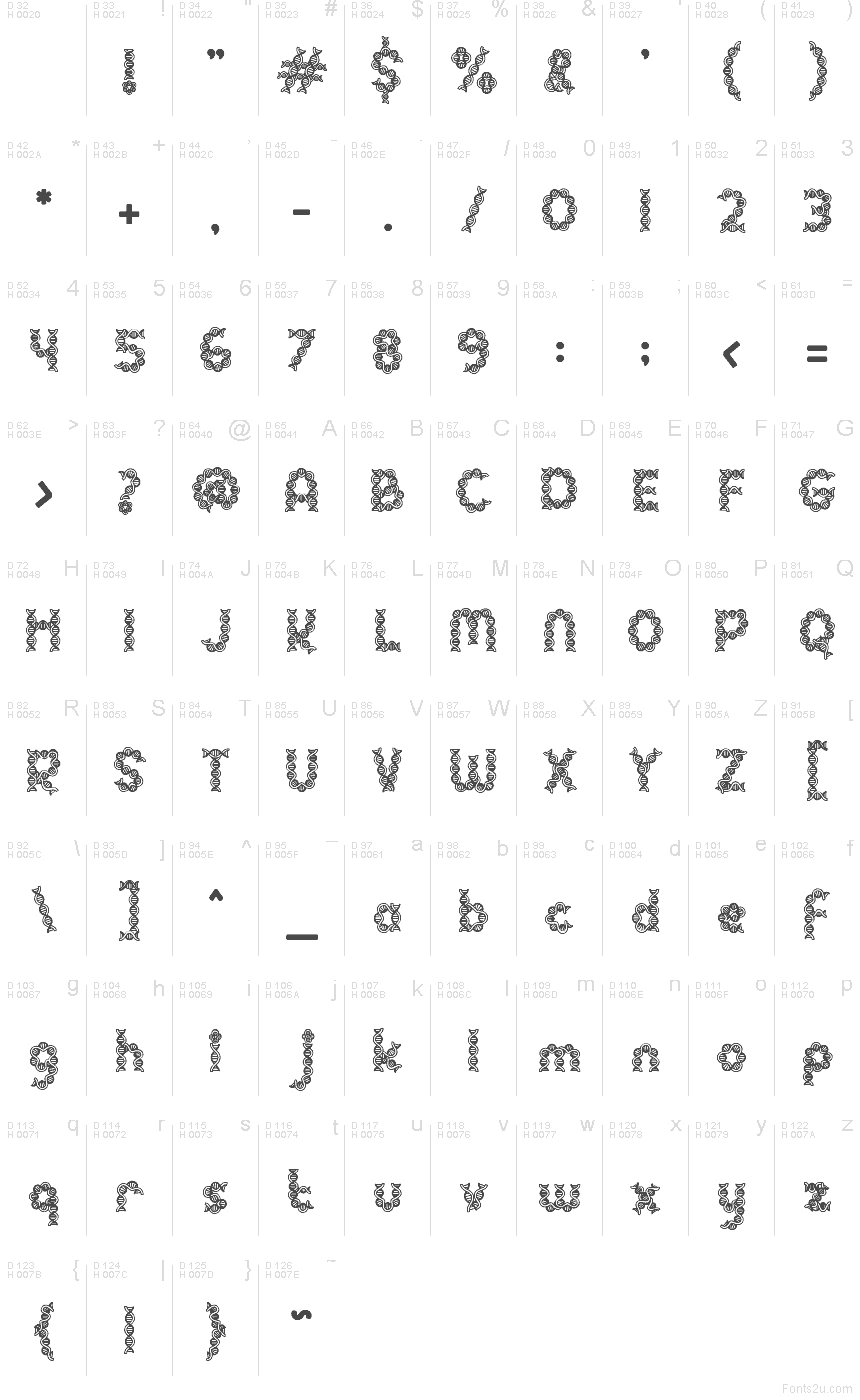
Clever Science DNA 2
Clever Science DNA 2 von Putracetol Studio ist eine kostenlose Display-Schrift mit DNA-Motiven, die an spielerische Laborplakate erinnert. Die Buchstaben sind aus ineinander verschlungenen Doppelhelix-Strängen und abgerundeten molekularen Formen aufgebaut. Dadurch wirkt das Alphabet weniger wie ein klassischer Zeichensatz und eher wie eine Reihe von Wissenschafts-Icons, die zu Initialen geformt wurden.
Dies macht sie zur idealen Wahl für STEM-Grafiken, Schulplakate, Wissenschaftsmessen, Museumsprogramme und Kinderbuchcover, bei denen das Thema eher freundlich als klinisch wirken soll. Da es sich um eine kostenlose Schrift handelt, eignet sie sich zudem hervorragend für kurze Titel, Logo-Badges und Monogramme, da das Helix-Muster schon bei wenigen Buchstaben seine Wirkung entfaltet.